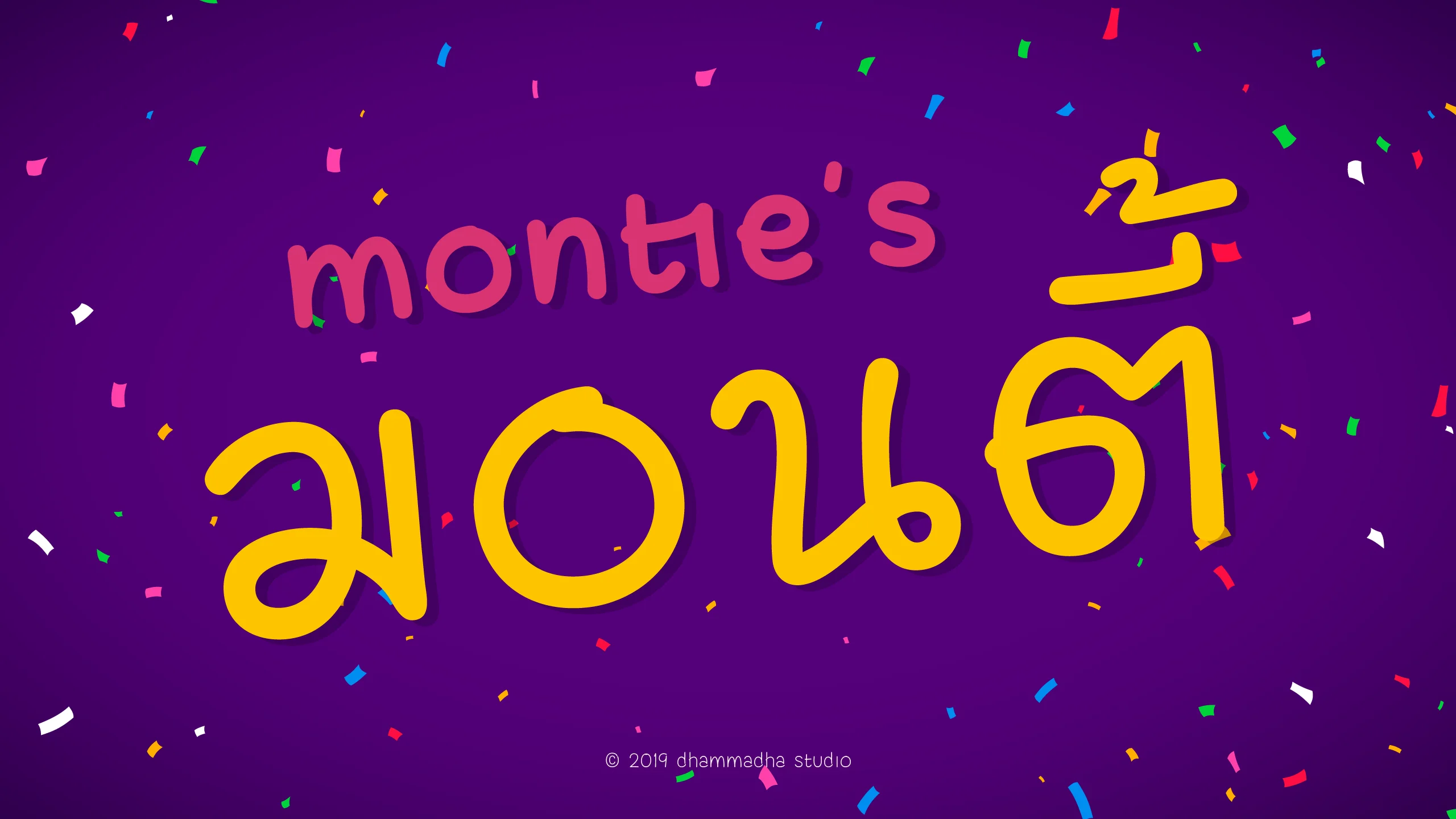
montie's
"มอนตี้ | montie's" คือชุดอักษรที่เข้ามาเสริมทัพกลุ่มฟอนต์ลายมือของ DHAMMADHA STUDIO ให้มีความหลากหลายและน่าสนใจยิ่งขึ้น แม้จะมีจุดเริ่มต้นจากแรงบันดาลใจที่ใกล้เคียงกับรุ่นพี่ในตระกูลเดียวกัน แต่เราได้นำมาพัฒนาและปรับเปลี่ยนรูปลักษณ์การนำเสนอใหม่ให้มีความโดดเด่นและแตกต่างออกไปจากเดิม เพื่อสร้างมิติใหม่ๆ ให้กับการสื่อสารที่ยังคงความรู้สึกเป็นธรรมชาติและมีชีวิตชีวา สะท้อนภาพลักษณ์ที่ดูเป็นกันเองแต่แฝงไว้ด้วยความทันสมัยที่เป็นเอกลักษณ์เฉพาะตัว ด้วยรูปทรงที่ถูกออกแบบมาให้ดูสบายตาแต่มีความน่าจดจำ ฟอนต์ชุดนี้จึงตอบโจทย์อย่างยิ่งสำหรับงานออกแบบที่ต้องการฉีกกรอบความซ้ำซากจำเจ ไม่ว่าจะเป็นการนำไปใช้ในงานอัตลักษณ์แบรนด์สไตล์ไลฟ์สไตล์ การจัดวางคำโปรยในสื่อโซเชียลมีเดีย หรือการสร้างสรรค์งานกราฟิกที่ต้องการความเป็นส่วนตัวและดูมีชั้นเชิง "มอนตี้ | montie's" จะช่วยยกระดับงานของคุณให้ดูมีความสดใหม่ เข้าถึงได้ง่าย และสร้างบรรยากาศที่น่าประทับใจให้กับผู้พบเห็นได้อย่างลงตัว